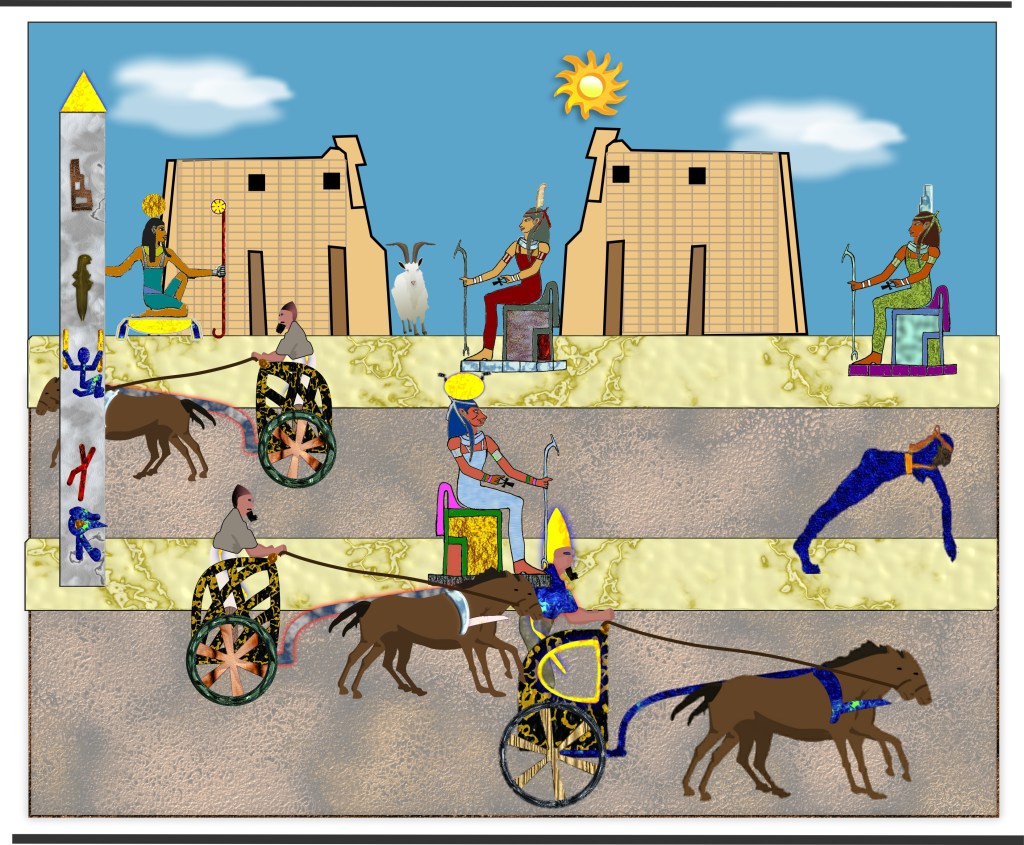
Ancêtre de l’Équitation
Ecriture et équitation.
Plus de 3 milliards d’êtres humains contemporains écrivent avec des alphabets ayant une origine unique. Pour retrouver celle-ci, il faut plonger au cœur de l’histoire de l’équitation !
Nous avons mené une enquête sur les rapports étonnants entre l’alphabet et le manège équestre, cet outil familier et pourtant non explicite, illustré de lettres.
Pour comprendre le mystère, il faut remonter aux sources de l’écriture, retrouver les significations, les symboles originels et déterminer quel peuple, quelle volonté politique et quelles intentions ont présidé à cette double invention.
AKDFVLPEXBSIRHGMC (?)
Que l’on pratique ou non l’équitation, cette série de lettres indispensable et passionnante nous intriguent. Nous passons devant en les lisant automatiquement, sans percevoir leurs parfaites positions, sans nous attarder sur leurs réelles significations.
Des lettres de l’alphabet, 17, ornent l’écrin de tous les efforts qui conduisent à l’équitation : le manège équestre.
C’est le haut lieu d’apprentissage et d’approfondissement, où l’humain communique des actions à l’équin et tente d’en comprendre les réactions et réciproquement.
Telle une mystérieuse cassette ou un plateau mythique, ce dispositif est étrange dans sa forme comme dans son décor. Il ne parle pas, il nous écrit, éveillant une curiosité avide de réponses à nos interrogations :
Le manège est bien connu, mais telle une mystérieuse cassette ou un plateau mythique, ce dispositif reste étrange dans sa forme comme dans son décor. Il ne nous parle pas, il nous écrit, éveillant une curiosité avide de réponses à nos interrogations.
Questions.
Nous avons six questions à nous poser, au minimum, pour tenter d’en savoir plus sur le manège équestre.
- Qui a rédigé cela ?
- A quel moment de l’histoire ?
- Pour nous dire quoi ?
- Pourquoi l’avoir fait ainsi ?
- Pour répondre à quel besoin ?
- Et enfin où ?
- Bonus : Comment est-ce parvenu jusqu’à nous ?
Bien entendu, les explications trouvées devront être complètes et les plus crédibles possibles dans l’exposé de la combinaison de leurs motivations. Notre quête est double puisqu’elle scrute les histoires intriquées de l’équitation et de l’écriture.